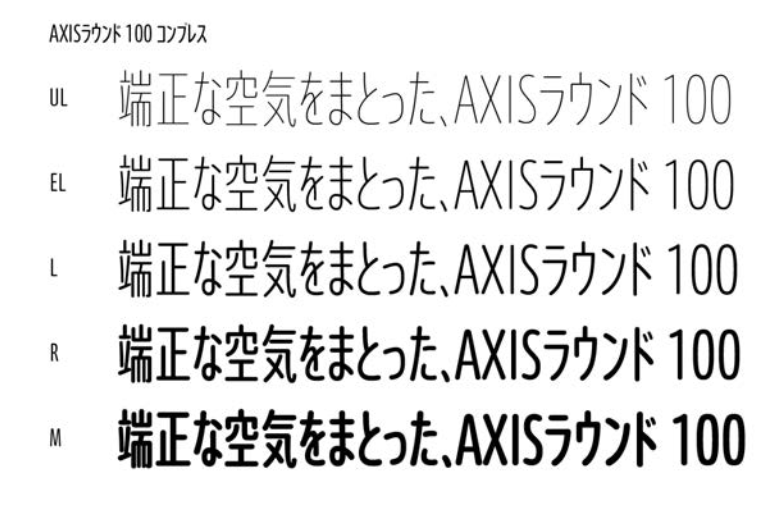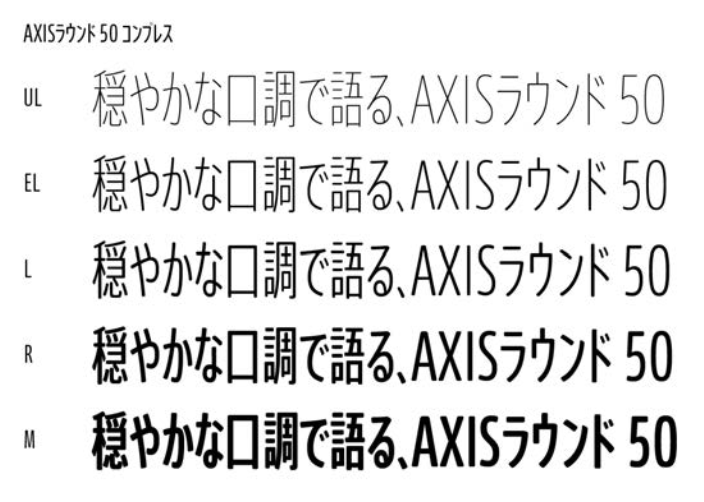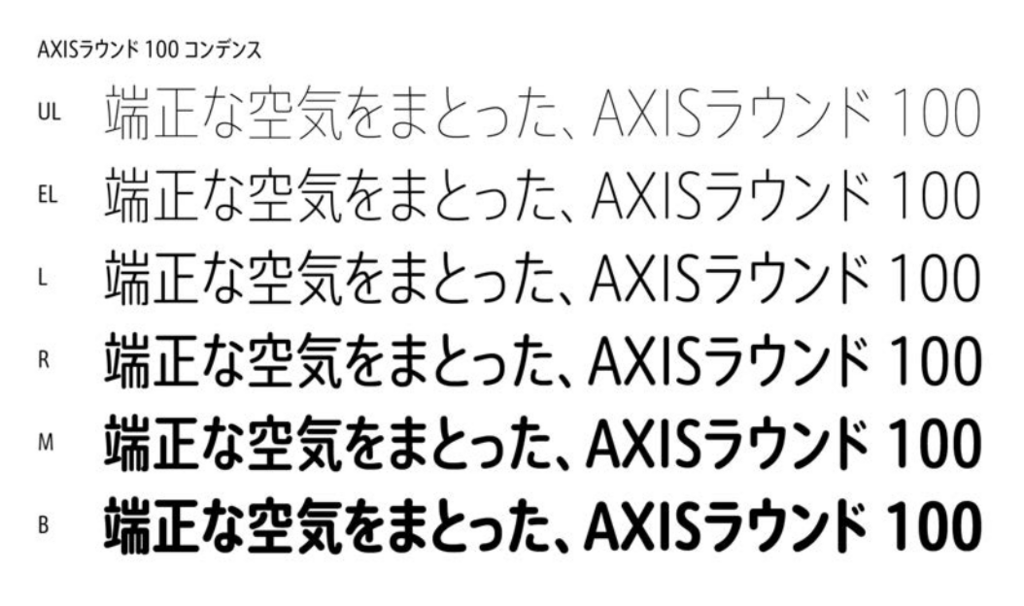
「AXISラウンド 50」、「AXISラウンド 100」のコンデンス版とコンプレス版を発表
タイププロジェクト株式会社は、「AXISラウンド 50」、「AXISラウンド 100」のコンデンスとコンプレスを同時発売することを11月6日に発表した。
コンデンス書体
基準となる書体に比べ、横幅を狭く設計した書体。狭く設計された中での最適な字形として画線の太さやバランスが調整されているため、通常の書体が長体をかけることで損なわれてしまう書体のデザインやバランス、視認性、可読性などを損なうことなく、表示できるようにデザインされているのが特徴。
AXISラウンド
AXIS Fontで表現できる世界観を更にに豊かににするために開発されたフォント。AXIS Fontのシャープな輪郭がわずかな丸みを帯びたAXISラウンド 50では、モダン・サンセリフのすっきりした印象を保ちながら柔らかな空気を醸しだす。AXISラウンド 100では、親しみやすさとともに、端正な空気をまとった「現代的な丸ゴシック」になっている。通常の丸ゴシックフォントとは違い、内径を丸めないことでモダン・サンセリフのシャープな表情を残している。
AXISラウンドにおけるコンデンスとコンプレス
AXISラウンドのコンデンスとコンプレスは長体に適した骨格で基本設計をおこなっており、印象的な文字でありながらも、心地よい自然なリズムを感じさせる。空間効率の良さと可読性の高さによってサインシステムなどで多く採用されているAXIS Fontコンデンスの機能に、親しみやすさという軸が加わり、活用シーンがさらに広がりをみせることになる。AXISラウンド 50、AXISラウンド100はのコンデンスはそれぞれ、漢字80%の長体に対して仮名を76%に、コンプレスは漢字60%に対して仮名を50%に設定している。
コンデンスのウエイトは、UL(ウルトラライト)、EL(エクストラライト)、L(ライト)、R(レギュラー)、M(ミディアム)、B(ボールド)の6種類。
コンプレスのウエイトは、UL(ウルトラライト)、EL(エクストラライト)、L(ライト)、R(レギュラー)、M(ミディアム)の5種類で構成している。
タイププロジェクトの代表取締役・鈴木功氏はプレスリリースにて、「AXISラウンドのコンデンスとコンプレスは、ニュートラルさが持ち味のAXIS Fontファミリーのなかにあってとりわけユニークな個性をもったフォントです。AXIS Fontのコンデンスとコンプレスは、空間効率の良さと可読性の高さによって、サインシステムなどで多く採用されています。AXISラウンドのコンデンスとコンプレスは、このような機能に加え、親しみやすさという特徴を備えていますので、活用シーンがさらに広がることを期待しています」と述べている 。